情熱と魂がフォントごとに
飛び出した!?
『文字のしおり』は、言葉がフォントごと切り取られたような巧緻で美しいデザインが特徴です。本好きの方にはもちろんのこと、その世界観は、どんどん広がり、愛の告白・ご当地のお土産・合格祈願など様々なシーンで活用いただけます。
そんな従来のしおりの概念を超えてきている栞をどうぞよろしくお願いします。
つないだ言葉が、人をつなぐ
デジタル時代が進む中でも、変わらない大切なものがあります。たとえ時代は移ろうとも、普遍的な価値を持ち続けるもの。
それは、人と人とのコミュニケーションです。文字のしおりは、シンプルでありながら深い!?意味を持つ贈り物です。
手渡すだけで気持ちが伝わり、相手の反応を直接感じることができる、新しいコミュニケーションツールです。
デジタルの便利さを享受しつつも、アナログの温かみを感じさせる文字のしおり。心を込めて、今この瞬間を大切にするための贈り物として、ぜひご活用ください。
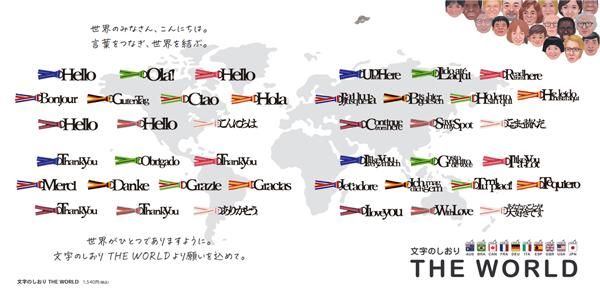
素材について
文字のしおりは、環境へ配慮した持続可能な天然セルロース素材から作られたファイバーを採用しています。この素材は環境への配慮を重視し、環境負荷の軽減に成功、強靭性・耐久性に優れた特徴を持ちます。それにより繊細なデザインの実現と自然と調和したエコフレンドリーなアイテムとなりました。